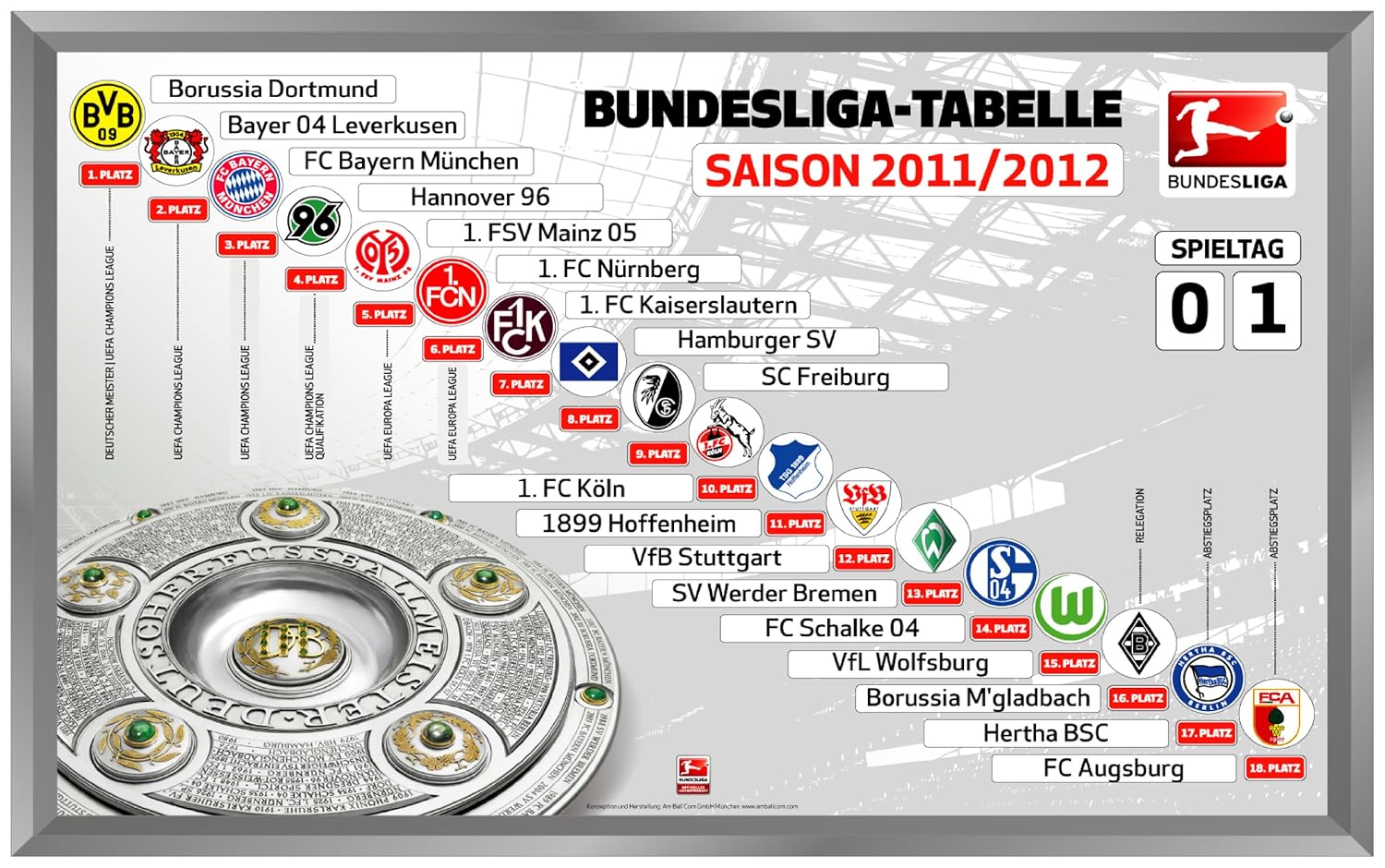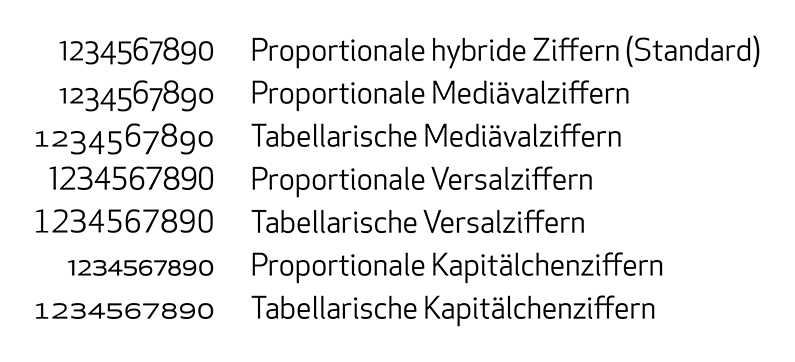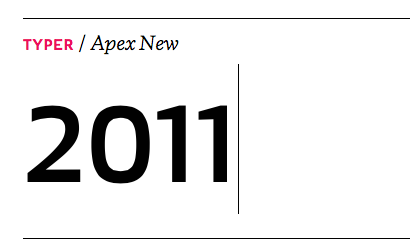
Schriftart der Bundesliga
Die Apex hat aber andere Zahlen … ???
die apex hat, wenn ich mich nicht verzählt habe, insgesamt sieben verschiedene ziffernsätze: mediävalziffern, versalziffern, kapitälchenziffern (jeweils tabellarisch und proportional zugerichtet) sowie die hybriden ziffern, die die vorschau zeigt (nur proportional zugerichtet). die bundesliga-tabelle verwendet offenbar die tabellarisch zugerichteten versalziffern.
Die lining numerals sind es. Danke für den Hinweis, die waren mir völlig entgangen.
hier noch für die freunde unterschiedlicher ziffernsätze:
was an der apex new übrigens auch toll ist: tabellarische ziffern sind nicht nur innerhalb einer strichstärke, sondern über alle strichstärken hinweg gleich breit zugerichtet (weight duplexing heißt das auf englisch). in immer mehr schriftarten ist das so, aber noch lange nicht in allen.